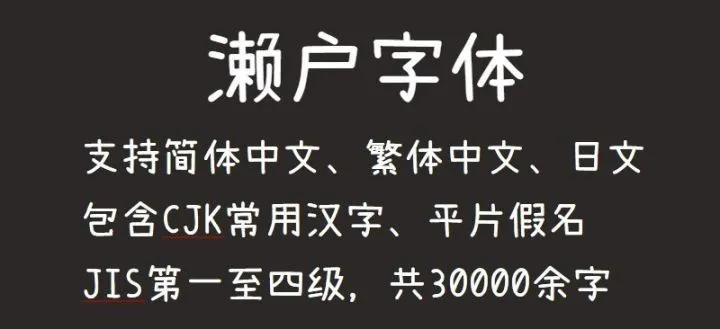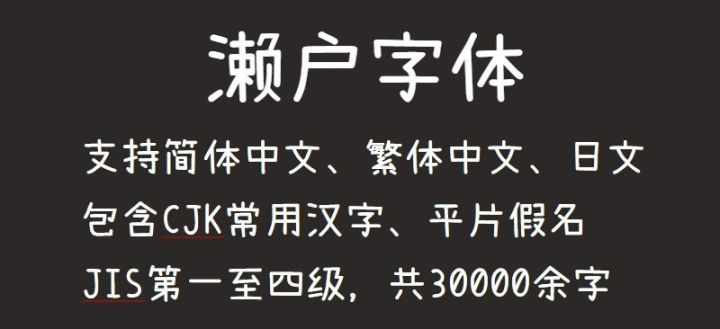
瀨戶字體(SetoFont),是一款偏可愛風的字體,是設計師個人手書,絲毫不造作,走的是一個好人緣天然呆的路線,甚至西文也很可愛,支持簡體中文、繁體中文、日文,包含CJK常用漢字、平片假名、JIS第一至四級,共30000餘字。這是由日本的一位業餘字體設計師(其實是以主婦的身份從事字體設計的)瀨戶のぞみ小姐所製作的。
瀨戶字體雖然支持中文,但是簡體中文容易缺字,如果你喜歡這個字體,可以移步到cjkfonts 全瀨體,cjkfonts 全瀨體是一款基於瀨戶字體透過深度學習智能造字的字體,彌補了瀨戶字體沒有的繁體及簡體字。
瀨戶字體,是一款偏可愛風的字體。